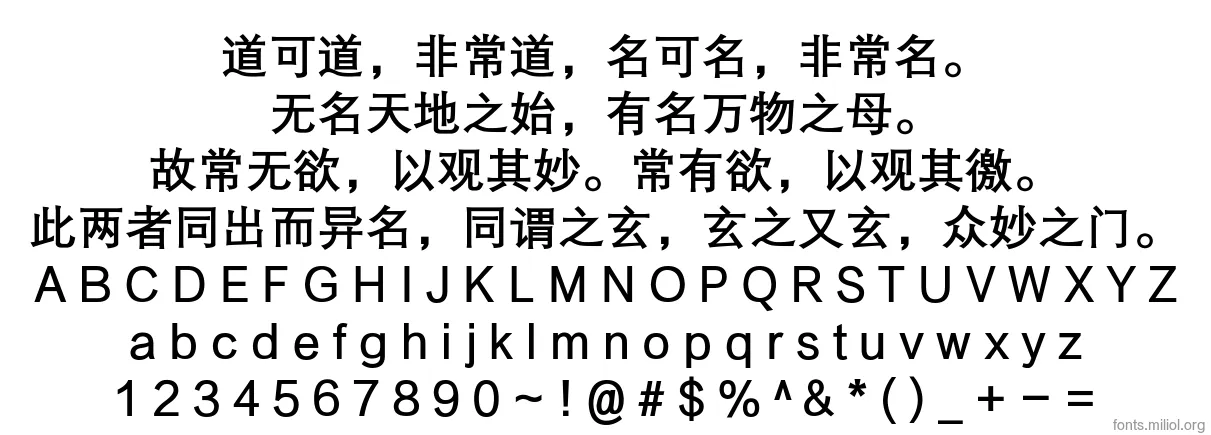
## 方正粗等线_GB18030字体:现代设计中的标准之选
方正粗等线_GB18030(FZDendXian-H_GB18030)是一款符合国家标准GB18030编码规范的等线体字体,由国内知名字库厂商方正字库精心设计制作。这款字体以其简洁有力的笔画特征和标准化的字符集支持,成为各类设计项目中的实用选择。
该字体采用等线体设计理念,笔画粗细均匀,转折处干净利落,整体呈现出稳重而不失现代感的视觉效果。作为GB18030标准字体,它完整支持包括汉字、标点符号、拉丁字母等在内的多种字符,特别适合需要处理繁简体中文混合排版的设计场景。其标准化的编码体系确保了在不同系统和软件中的兼容性,避免了常见的乱码问题。
方正粗等线体在平面设计、网页排版、印刷出版等领域都有广泛应用,尤其适合需要清晰易读性的标题文字和导视系统设计。字体文件命名中的FZCDXGB40标识了其特定的版本信息,用户在选用时应注意核对版本兼容性。这款字体体现了方正字库在中文数字化领域的专业水准,是设计师值得信赖的字体资源之一。